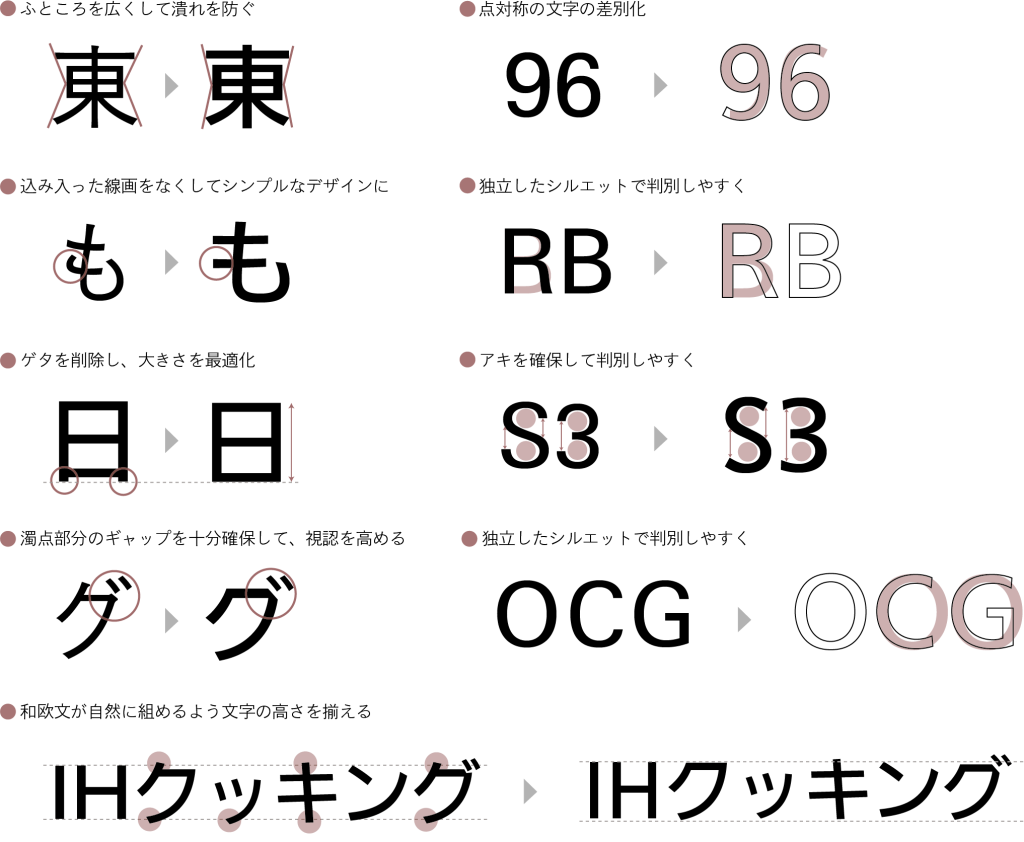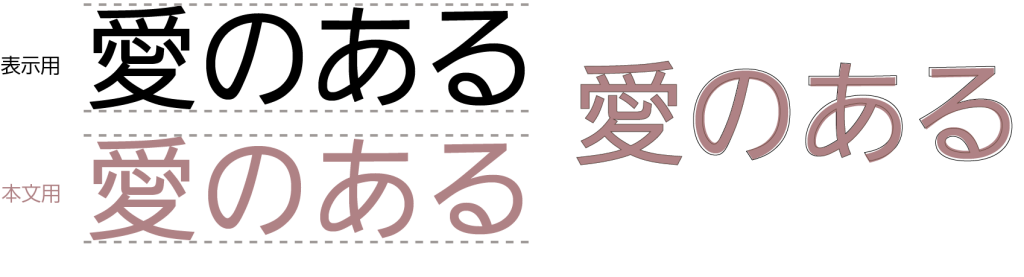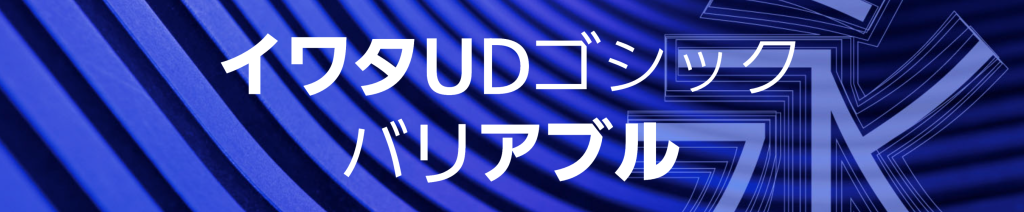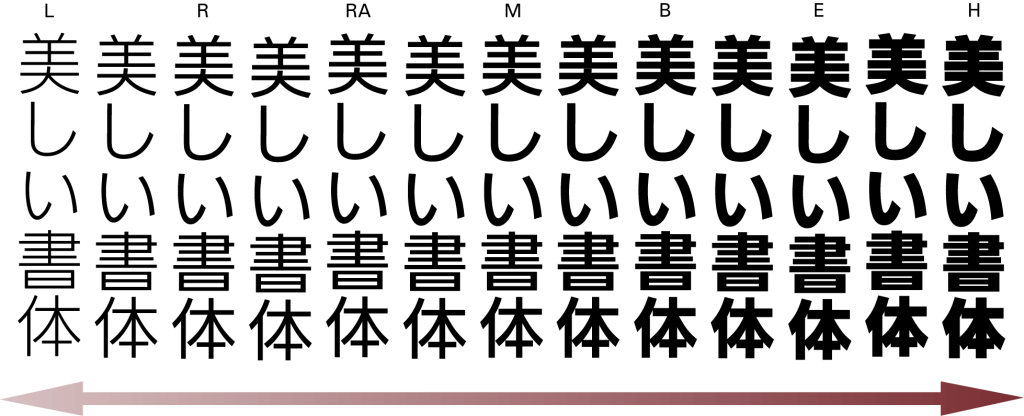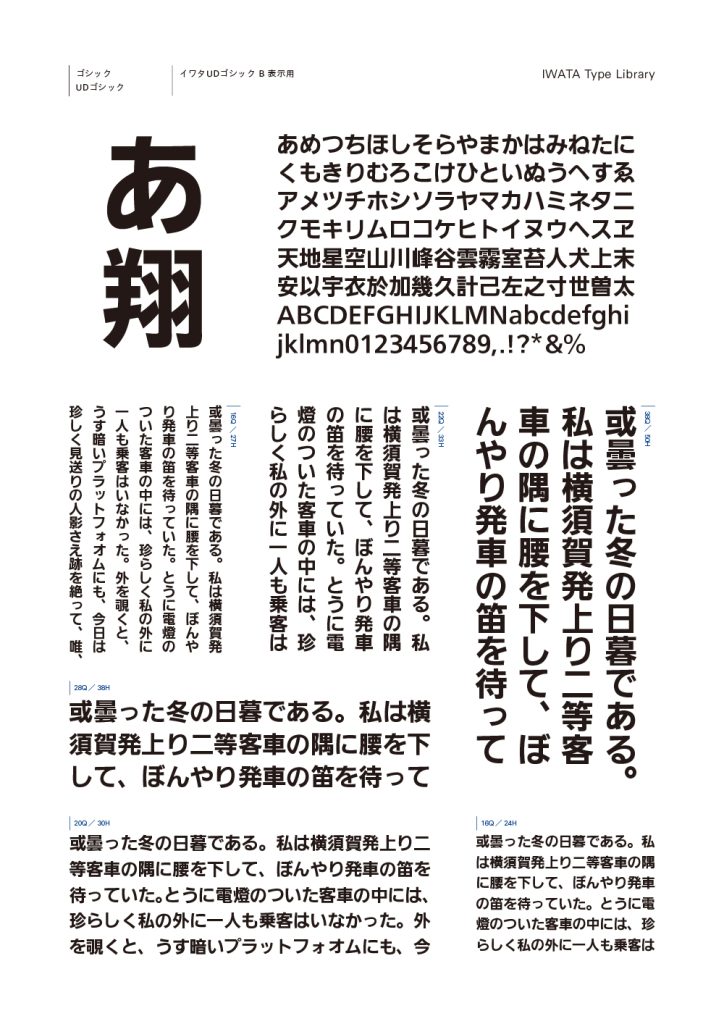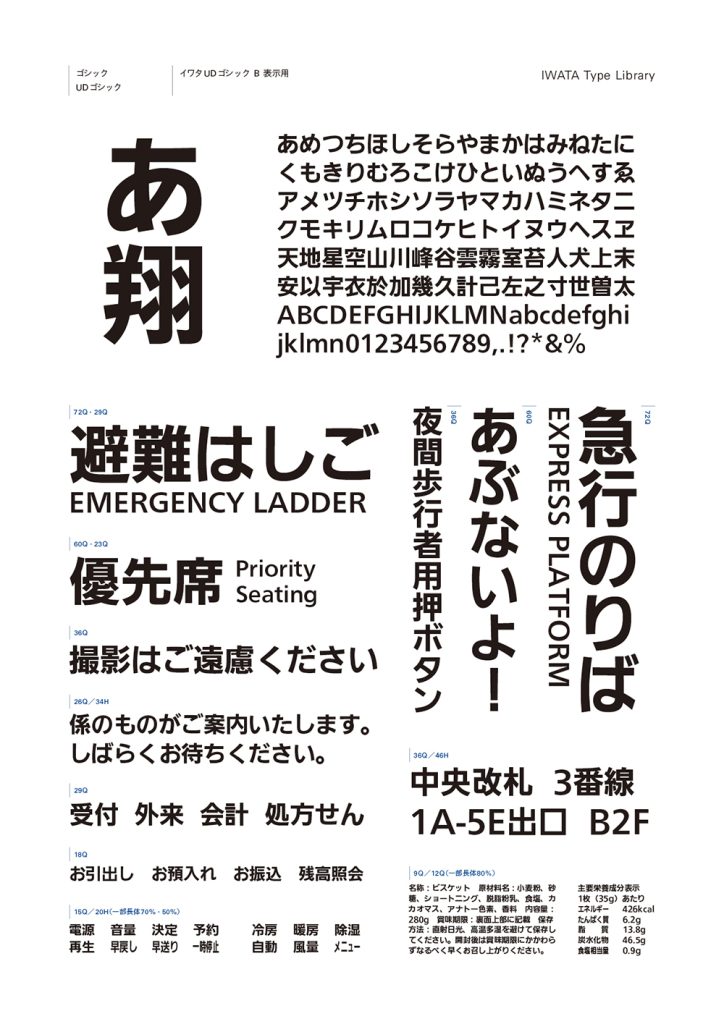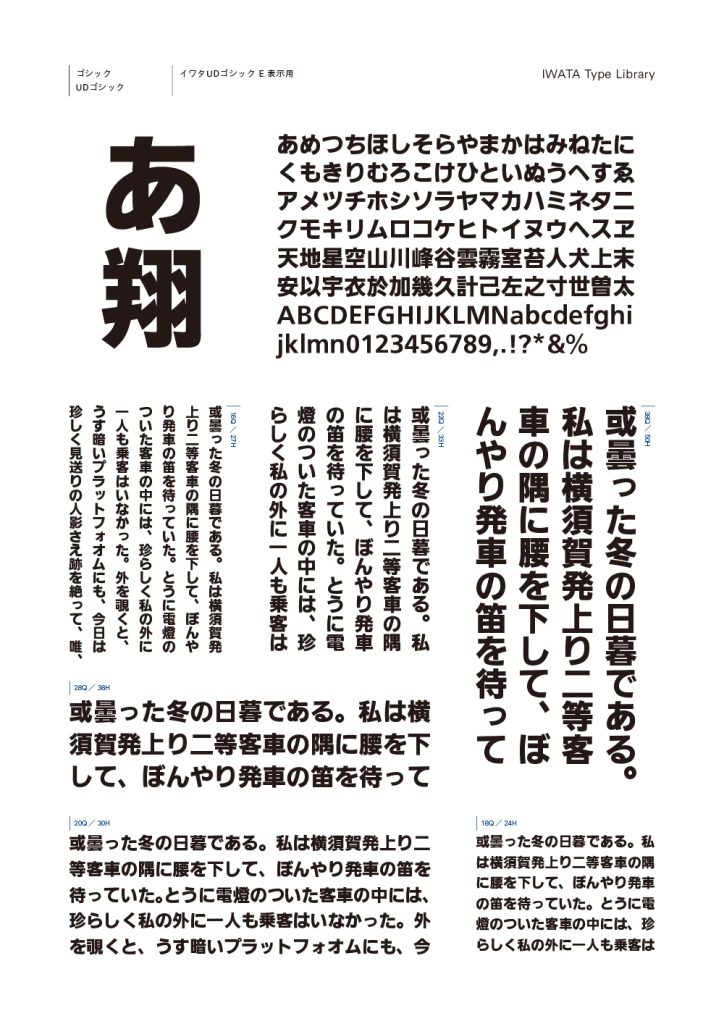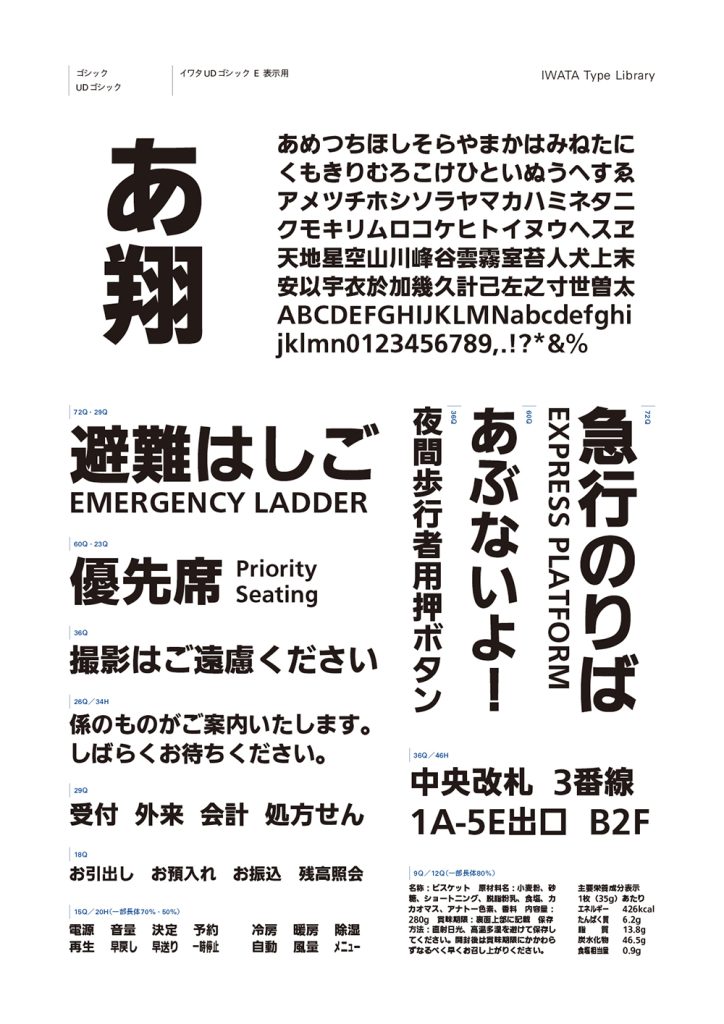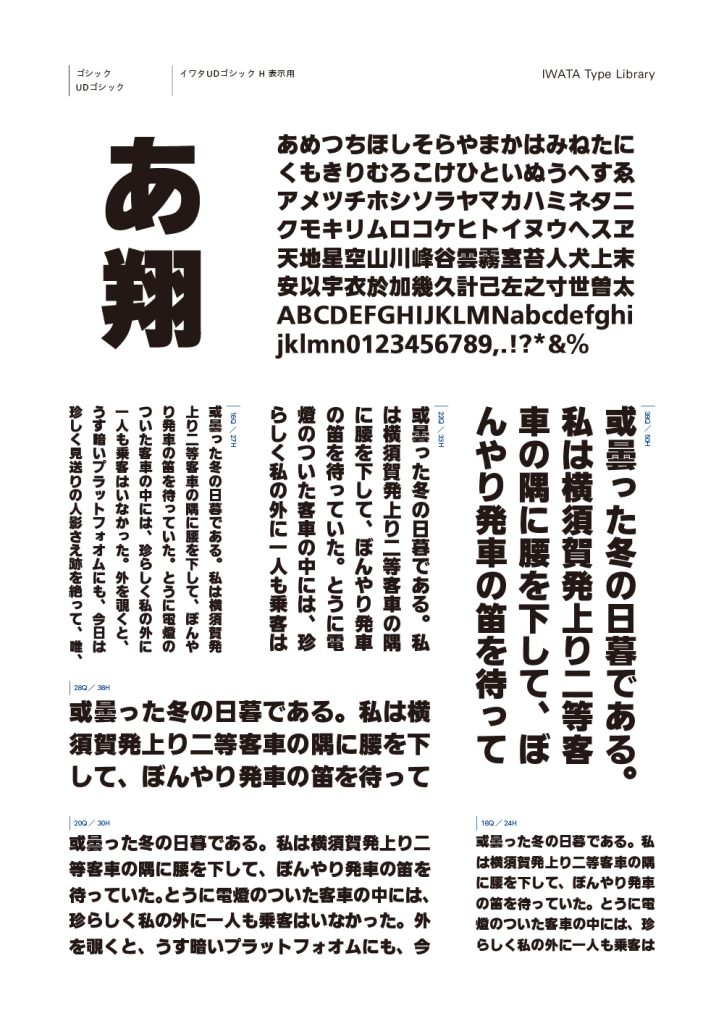
松下電器株式会社(現、パナソニック株式会社)と共同で開発した、すべてのひとに見やすい、読み
やすいフォントを目的に、日本で最初にユニバーサルデザイン(UD)視点で開発されたゴシック体です。「表示用」は視認性と判読性に重点を置いて仮名や欧文を大きくデザインし、単語や短い文章での使用に向いています。「本文用」は長文での読みやすさを追究し、「表示用」よりも仮名や欧文が小さく設計されています。
開発の背景
高齢化社会が進んだ現在、老眼、白内障等々、加齢による視力の低下に悩む人が急増しています。
一方で製品の多機能・高機能化、小型化、デジタル化が急速に進んでいます。 このような環境においては、文字こそUD の視点で作られたものが必要と考え、誰にとっても読みやすい文字、「イワタUD フォント」を開発するに至りました。
一般的な書体での読みやすさ、見やすさの課題
書体デザインのポイント
誤読を防ぎ読みやすさを向上させるために、デザインにいくつもの工夫がされています。
※「イワタ中太ゴシック体オールド」・「イワタ新ゴシックM」と「イワタUD ゴシックM 表示用」
を比較しています
「表示用」は視認性と判読性に重点を置いて仮名や欧文が大きくデザインされています。「本文用」は長文での読みやすさを追究し、「表示用」よりも仮名や欧文が小さく設計されています。
イワタUDゴシックバリアブル
「イワタUD ゴシック表示用」はバリアブルフォントもご用意しています。フォントのデザイン
を損なうことなく文字の太さを「L」から「H」の間でシームレスに変更することができます。